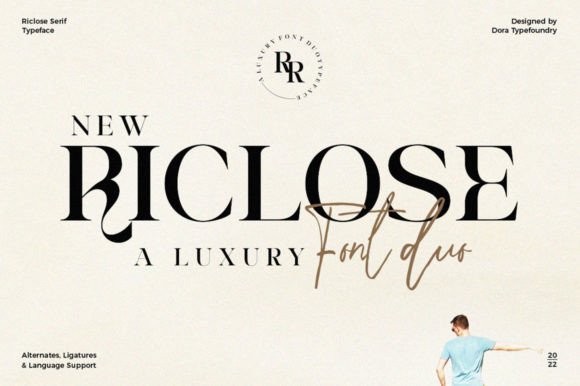
Riclose Duo
適切なデザイン要素を見つけるのは難しい場合がありますが、Riclose Duoは作品を即座に引き立てる優れたコレクションを提供します。
POD(オンデマンド印刷)製品、結婚式の招待状、またはソーシャルメディアのグラフィックを作成している場合でも、Riclose Duoは理想的です。